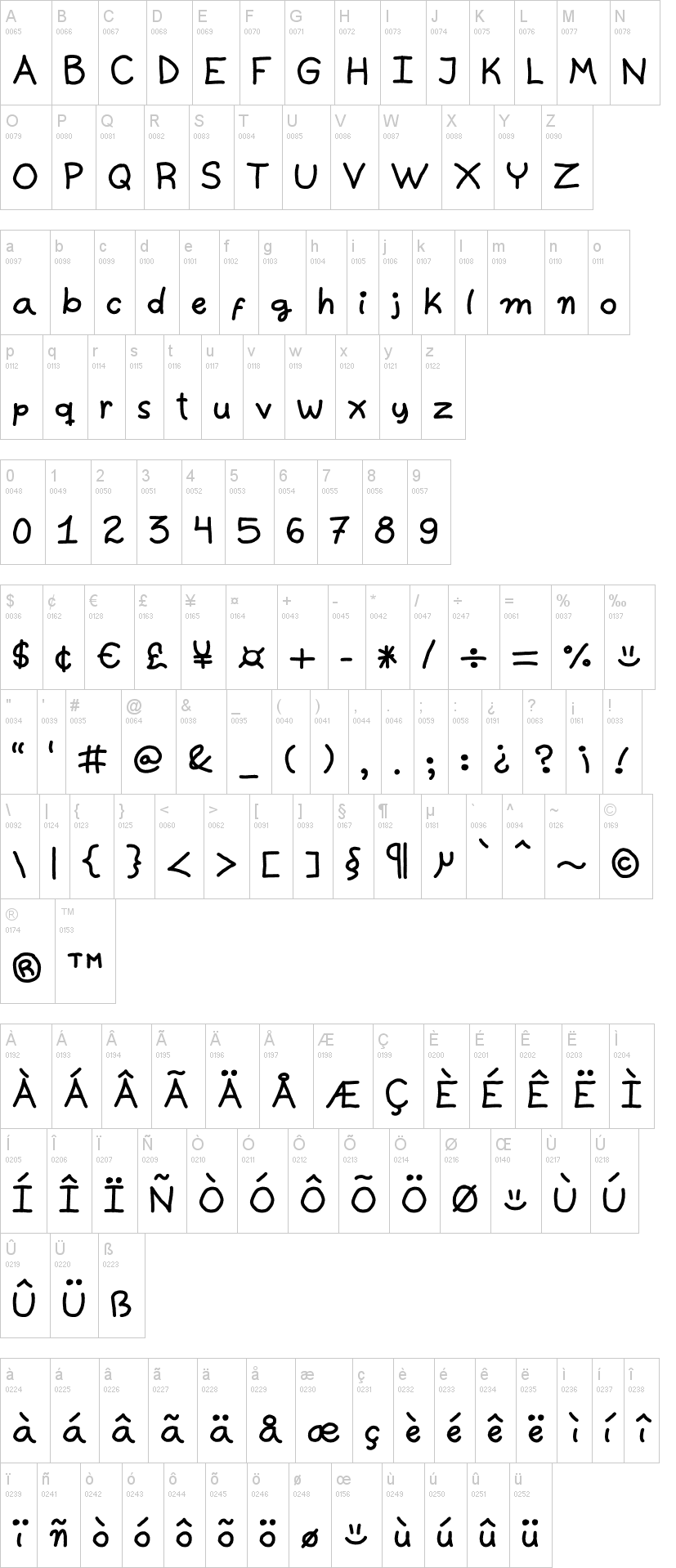
Note of the authorTipografía hecha a mano, llamada "castillo" incluye acentos, signos de interrogación y exclamación iniciales, entre otros. Espero que te guste. 100% gratis. Utilízala en cualquier proyecto comercial o privado. Si quieres hacer una donación, contáctame.